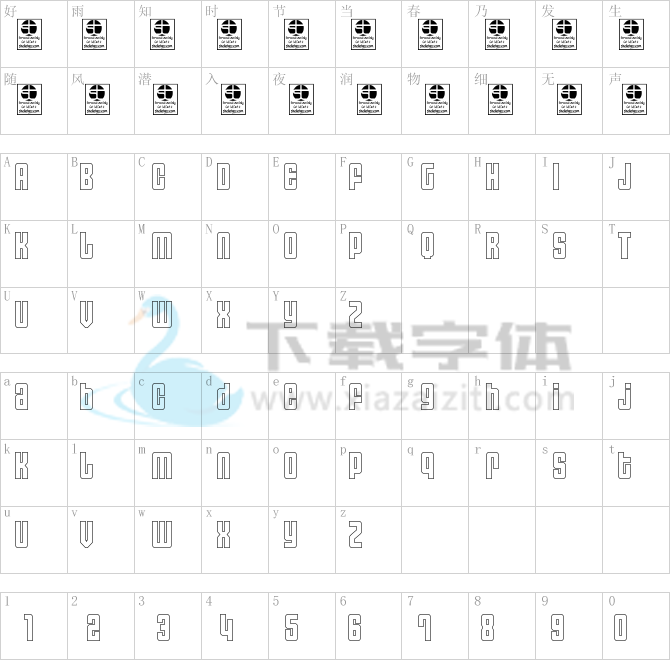
Asectica Outline Demo.otf字体下载,这款字体结构工整、笔画清晰,兼顾美观与易读性,适用于标题、正文、海报、包装、LOGO 等多种场景。字形优雅稳定,风格百搭耐看,适配日常排版与创意设计,让文字呈现更舒适、更具质感。Asectica Outline Demo.otf字体下载一笔一画,皆是细节,以均衡的比例、流畅的线条打造舒适视觉体验,字形端正大气,风格简约现代。无论是商业设计、品牌宣传还是日常排版,都能轻松驾驭,让文字更有格调与力量。Asectica Outline Demo.otf字体下载字体下载。
Asectica Outline Demo.otf图片展示
Asectica Outline Demo.otf映射图